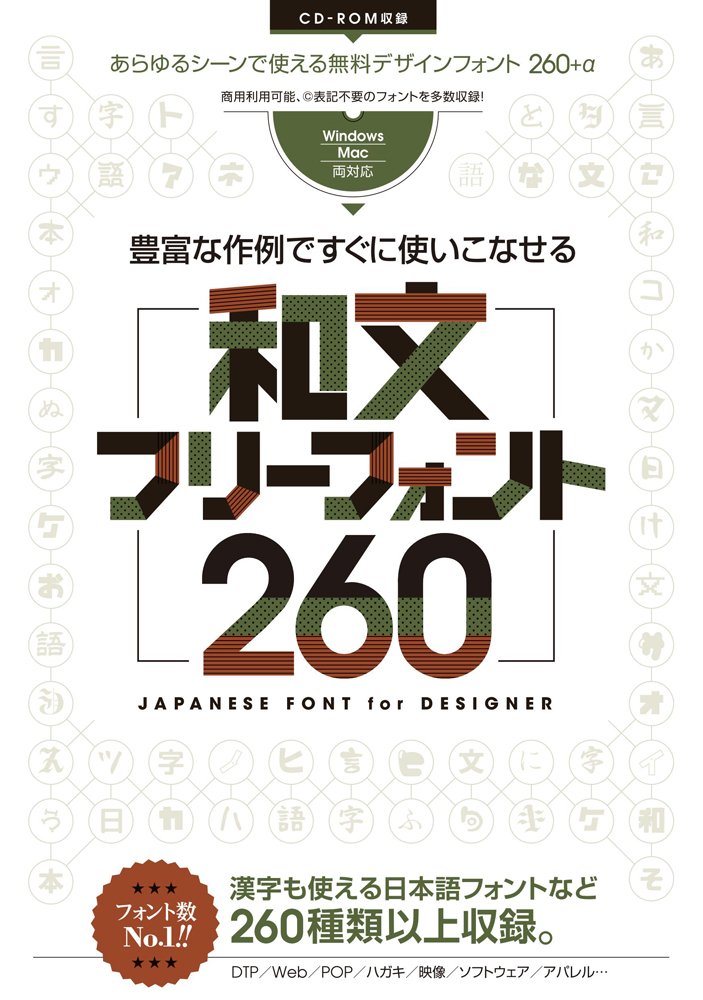
豊富な作例ですぐに使いこなせる 和文フリーフォント260
260書体以上の和文フリーフォントを収録したGOLDEN AXE著書による「豊富な作例ですぐに使いこなせる 和文フリーフォント260」がstandardsから2017年3月17日に発売を開始した。
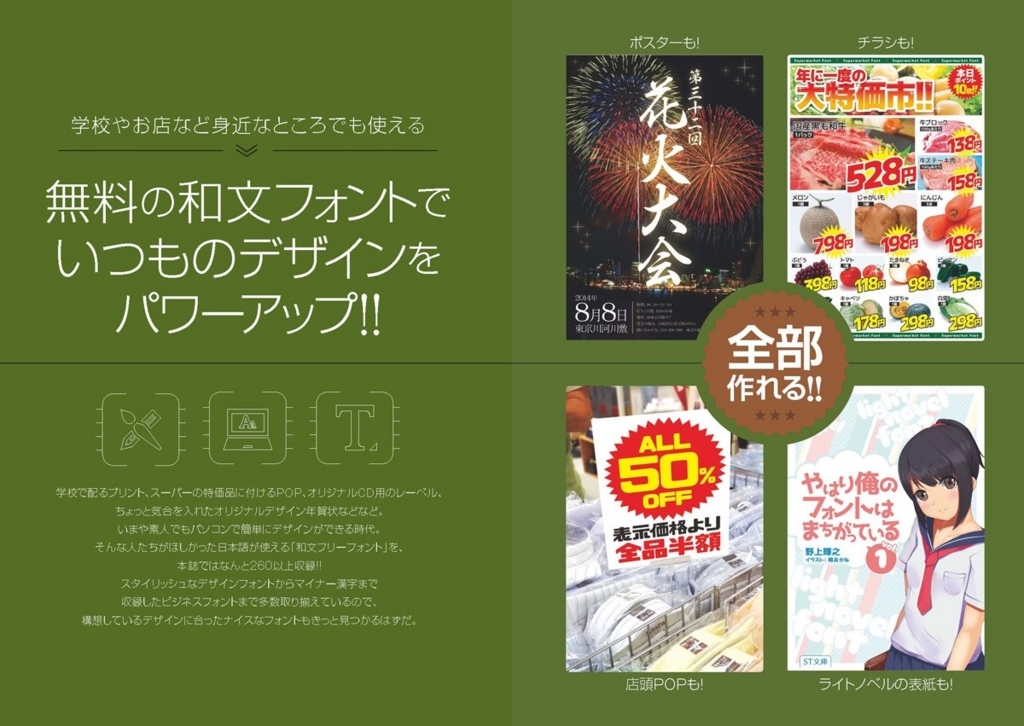
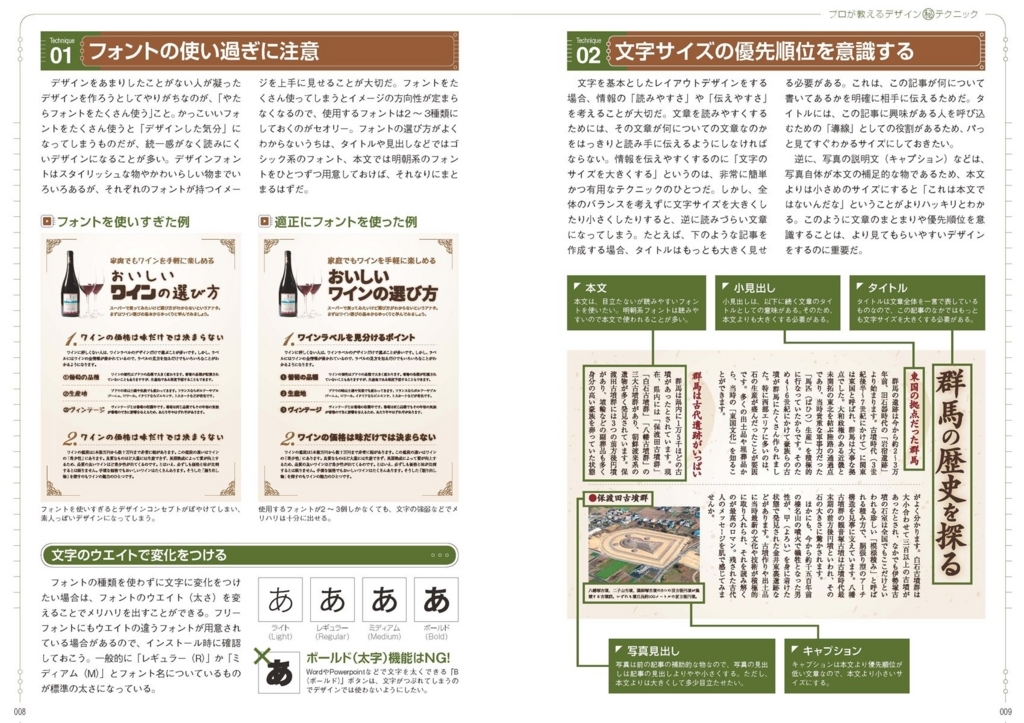
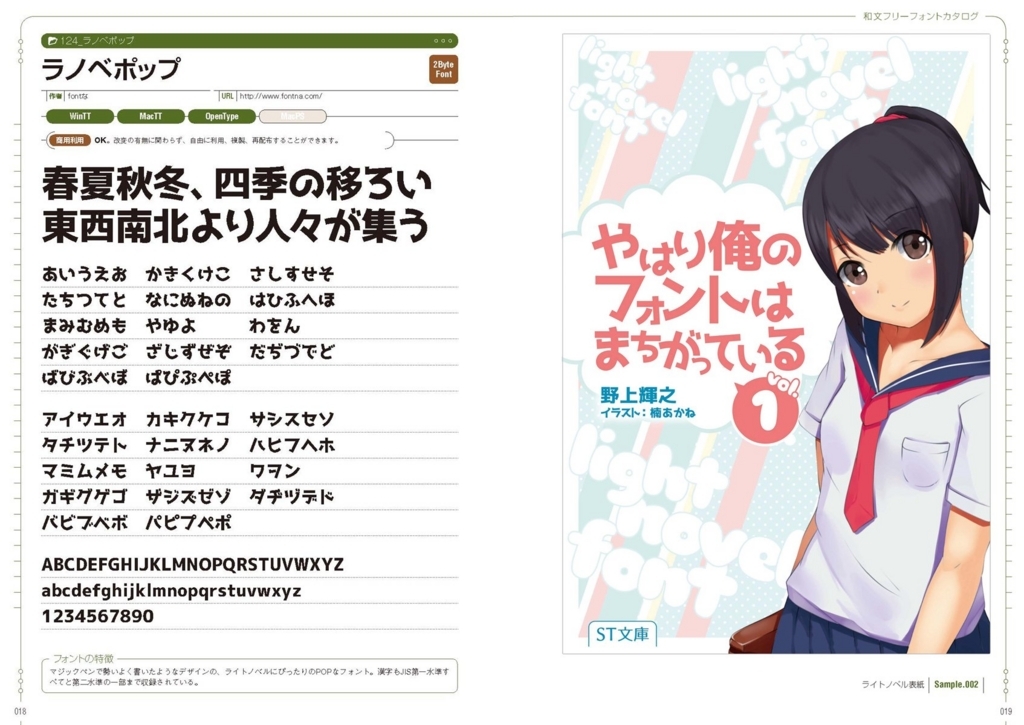
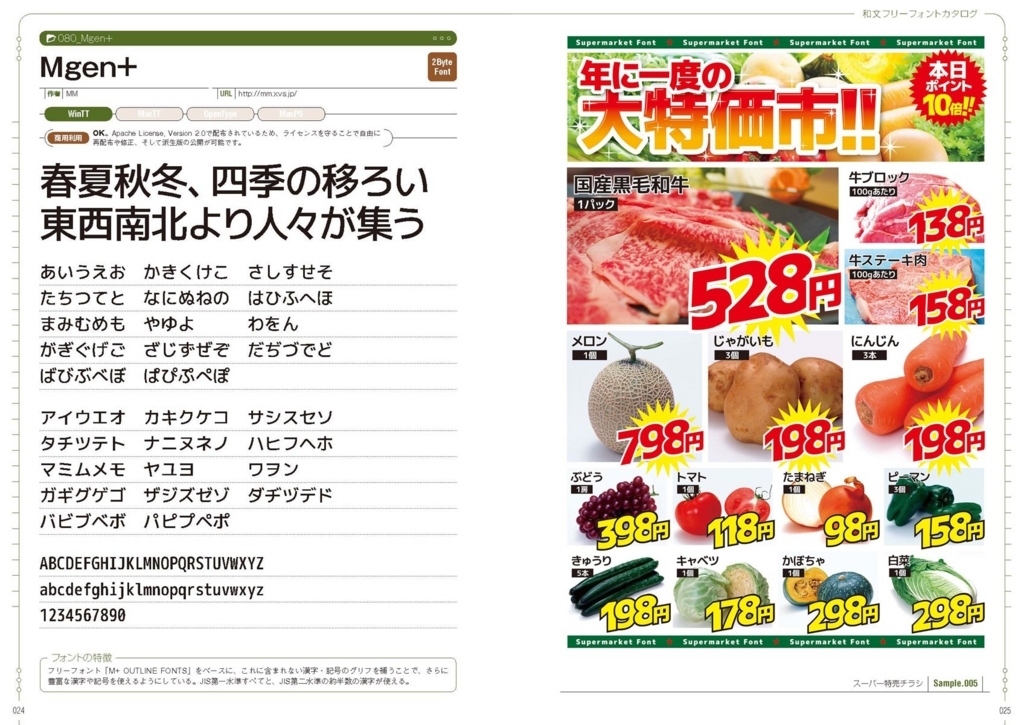
アマチュアからプロまで、デザインワークに使える無料の和文フォントを260種類以上紹介&収録!
漢字も使えるフォント、商用利用もOKなフォントなどの日本語フリーフォントが多数!
ホームページやチラシ、ポスターやポップ、名刺、年賀状づくりなどに思わず使いたくなる
フォントを厳選しました。チラシやセレクトショップのポップに使えそうなフォント、ペン字のようなフォント、
女子高生の手書き文字風フォント、同人誌の表紙に使えそうなフォントなど、
デザインに使いやすい個性的なフォントを260種類以上しています。
また、プロデザイナーによるフォントの使用例がわかるデザインサンプルも
多数、掲載しましたので、フォントの効果的な使い方が一目でわかります。
ちょっとした手書き文字をデザインで使いたいとき、ユニークなグラフィックを
つくりたいときなどに、とても便利な1冊です。